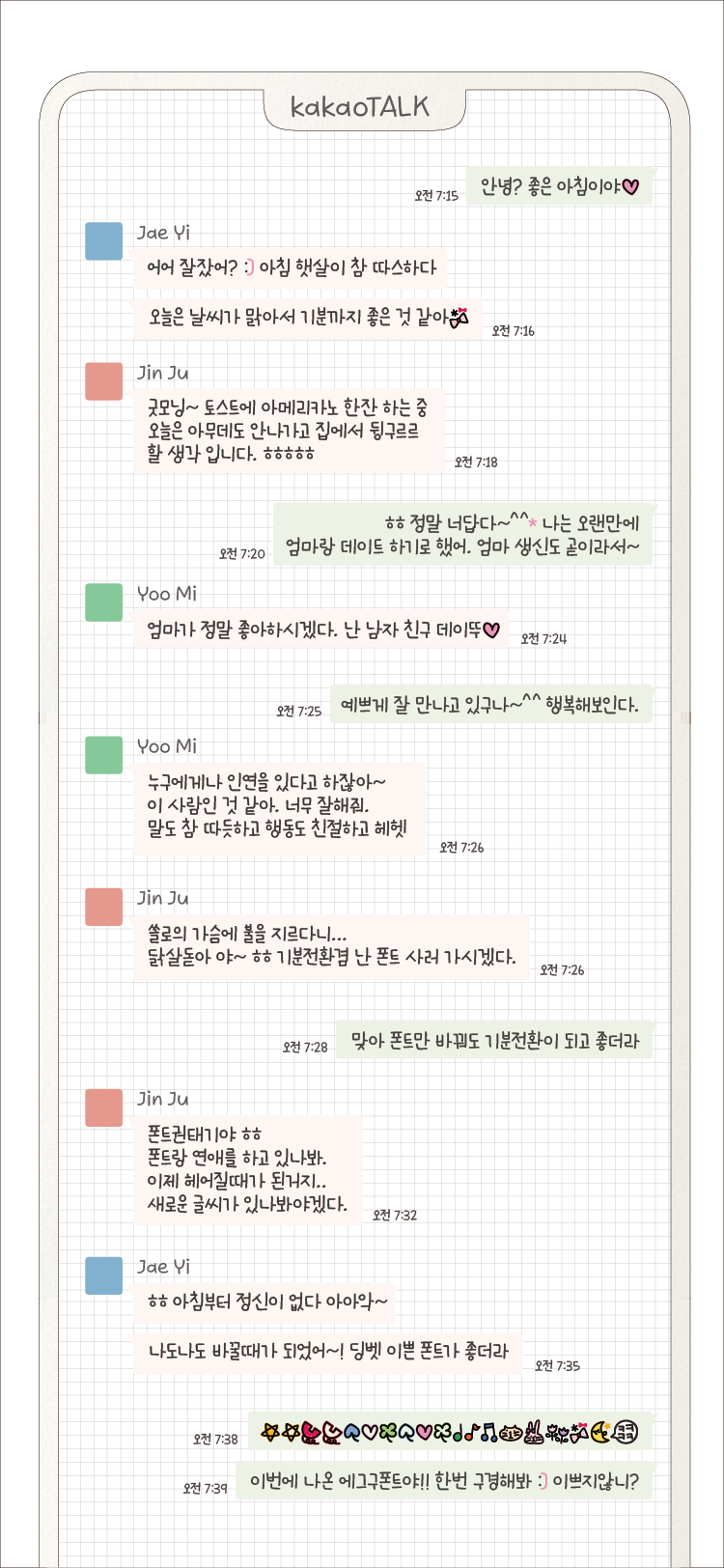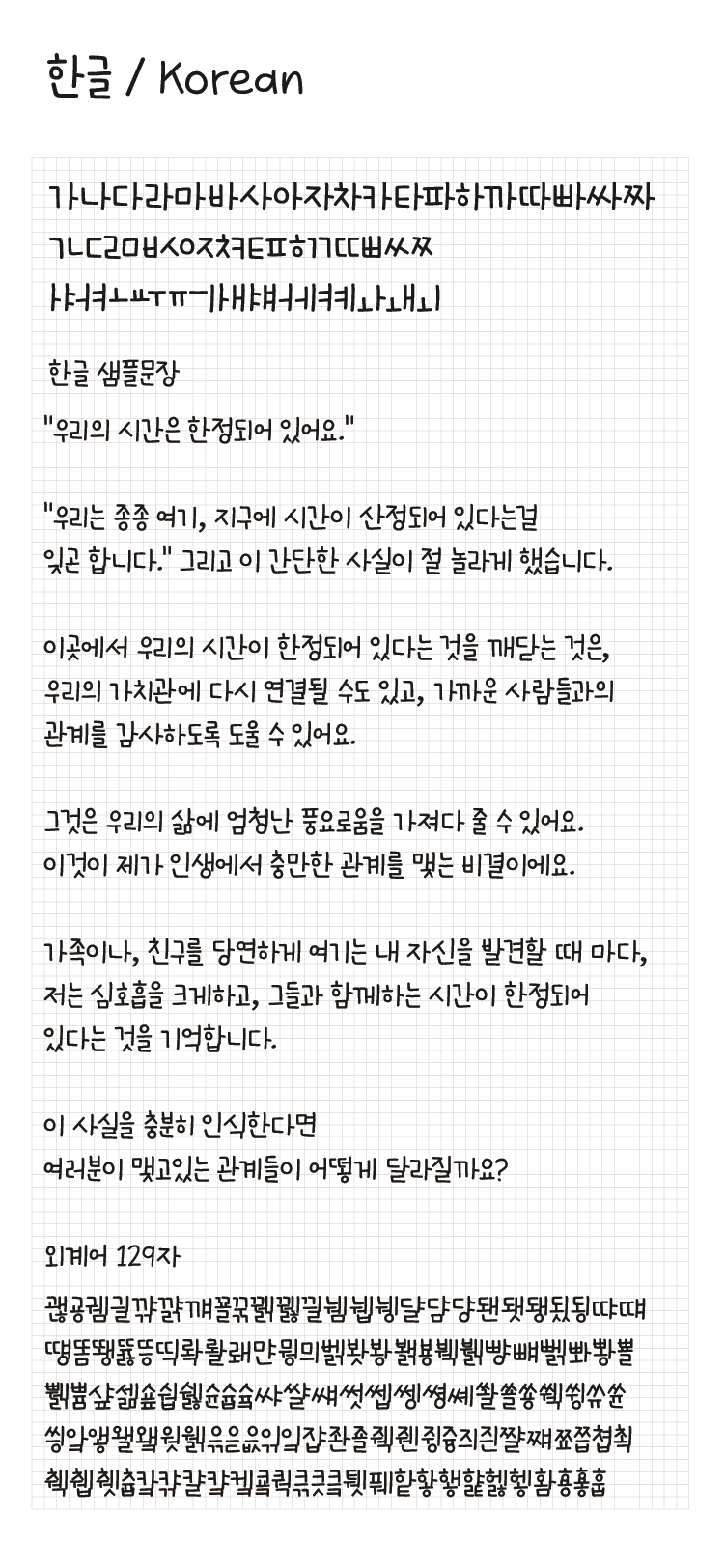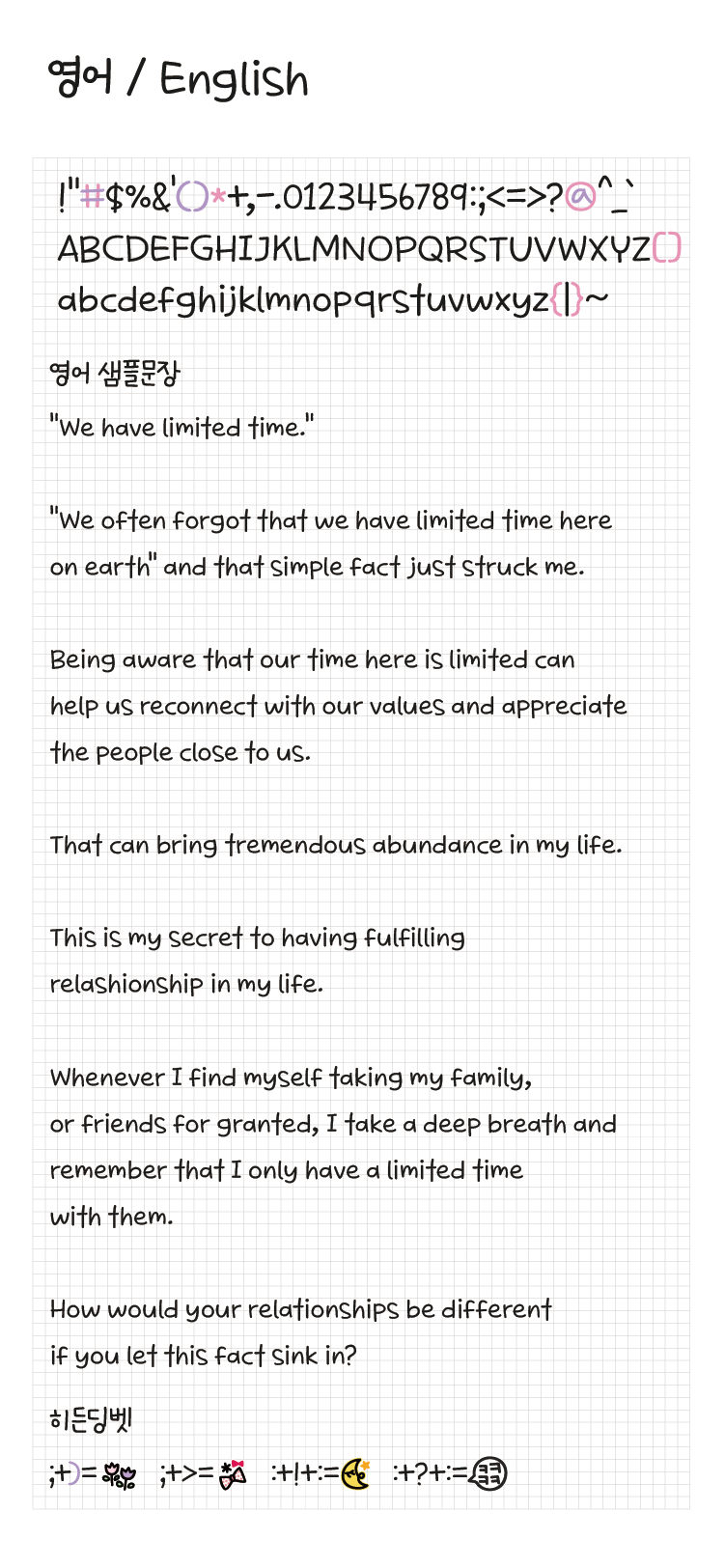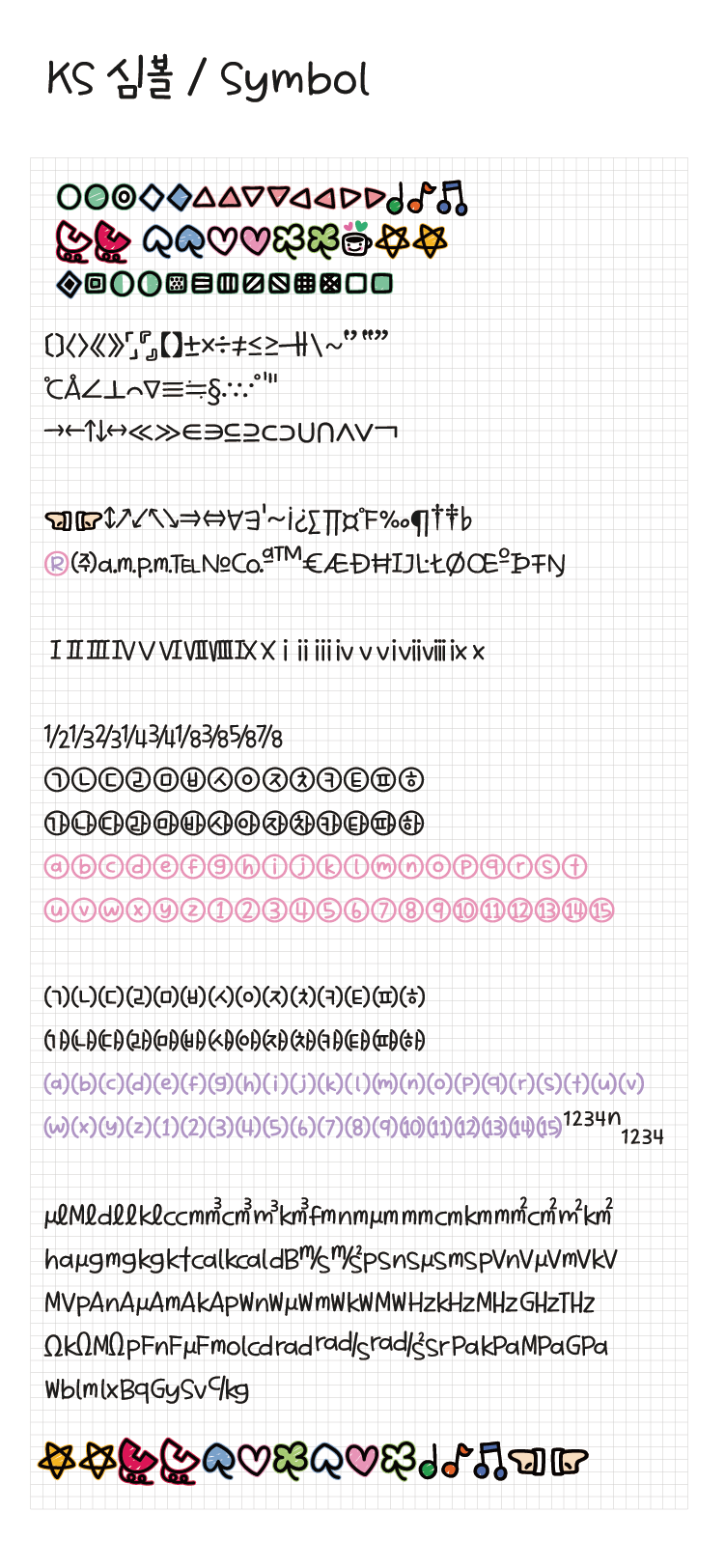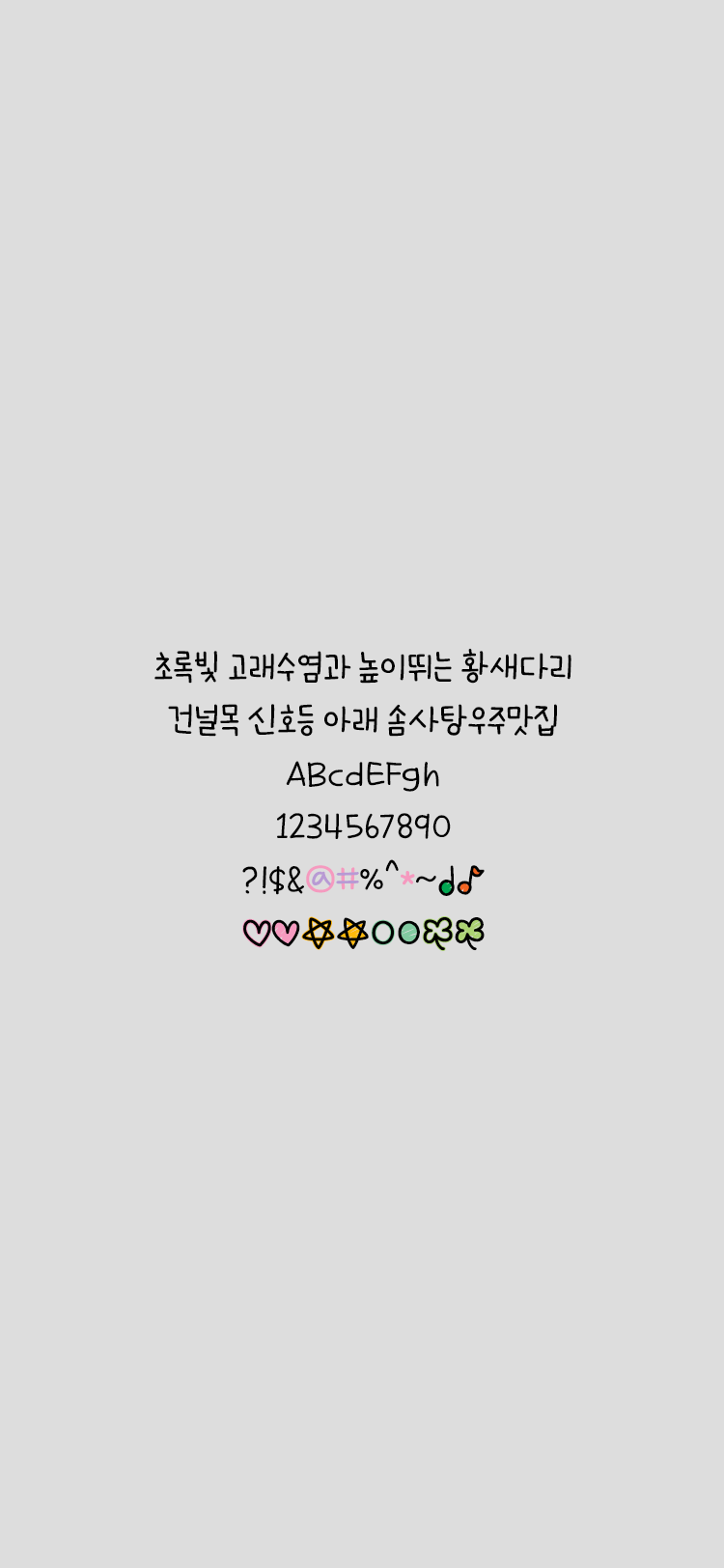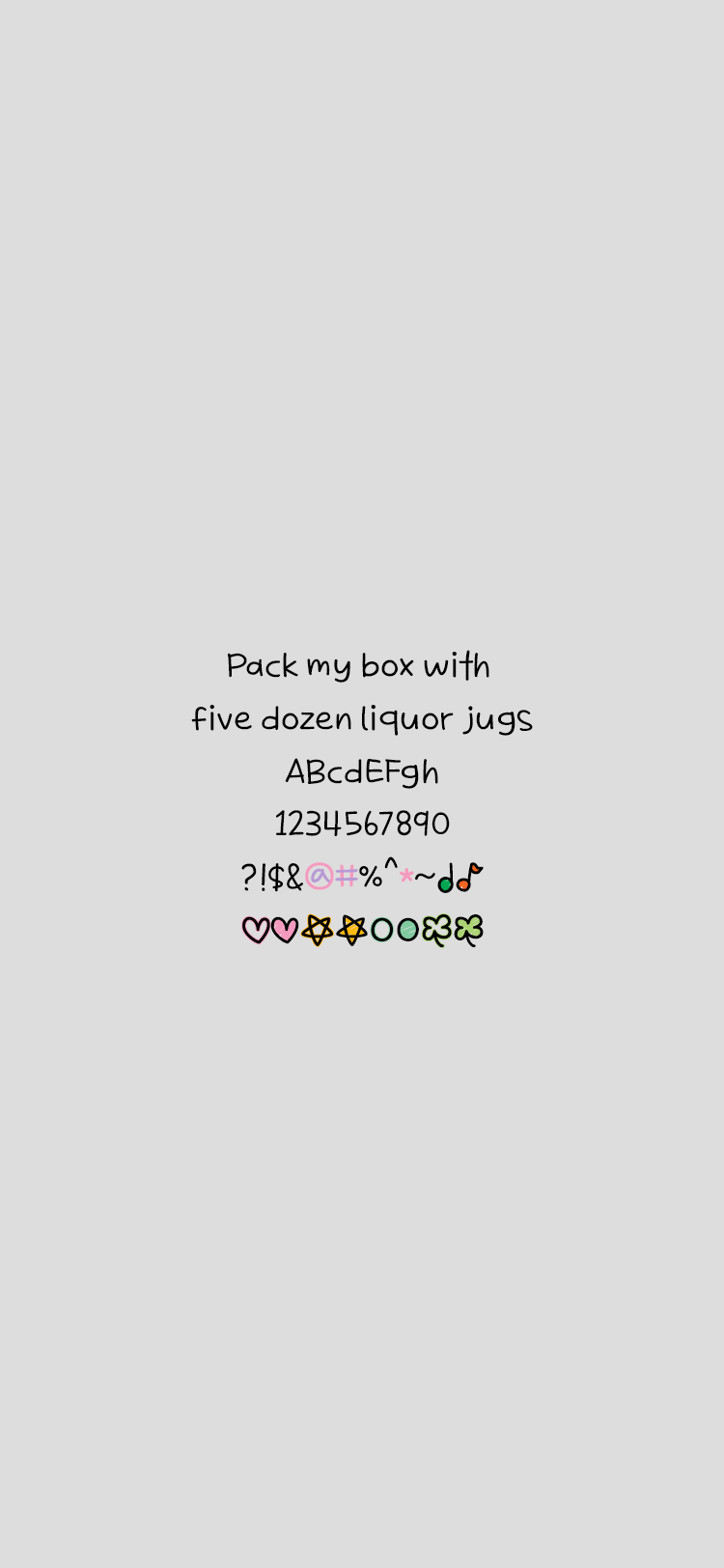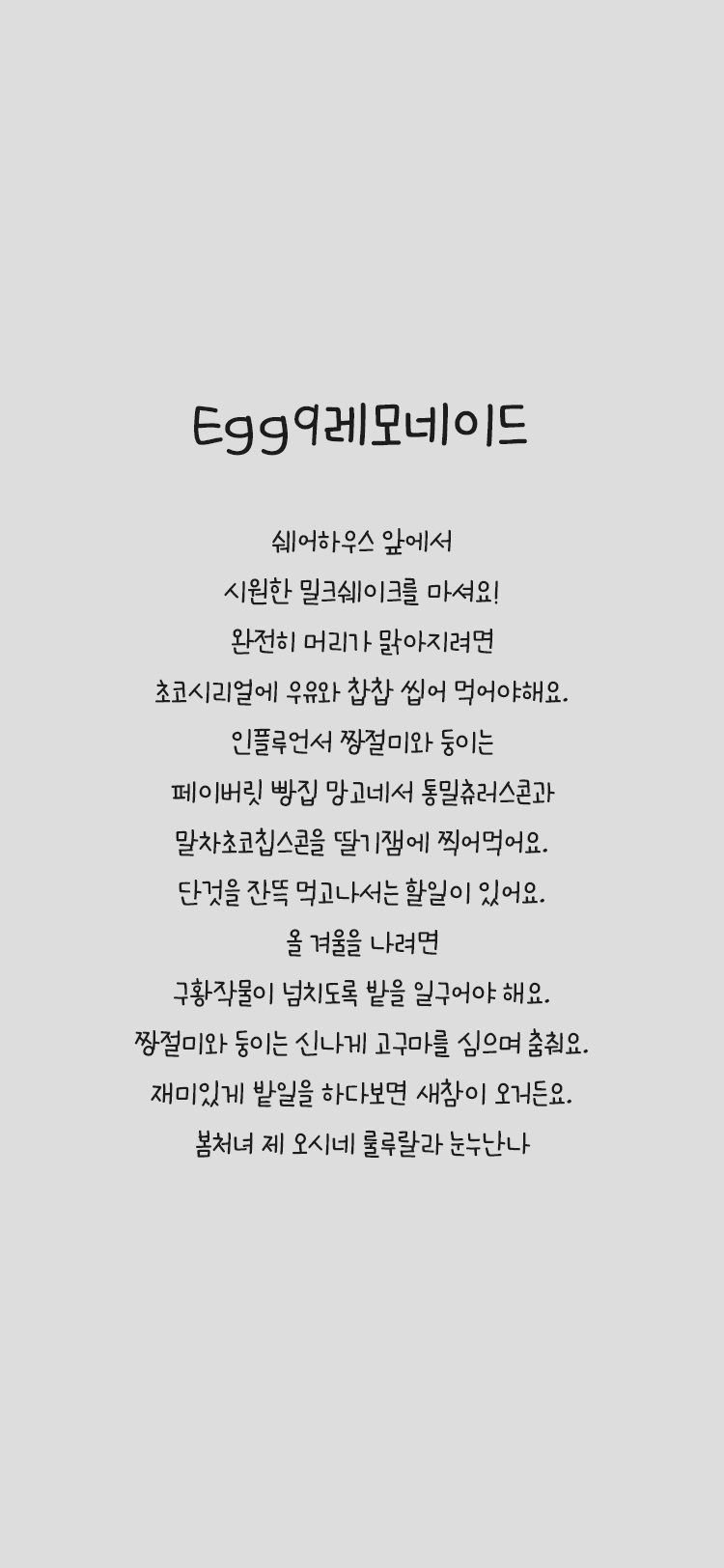
Egg9 레모네이드
Egg9 레모네이드 font in use
아기자기한 손글씨 스타일입니다. 히든딩벳의 경우 ;> ;) :!: :?: 입력하시면 나옵니다.
이 글꼴은 색상을 지원하지만 일부 앱에서는 작동하지 않을 수 있습니다.
• Egg9 레모네이드 / Egg9 Lemonade